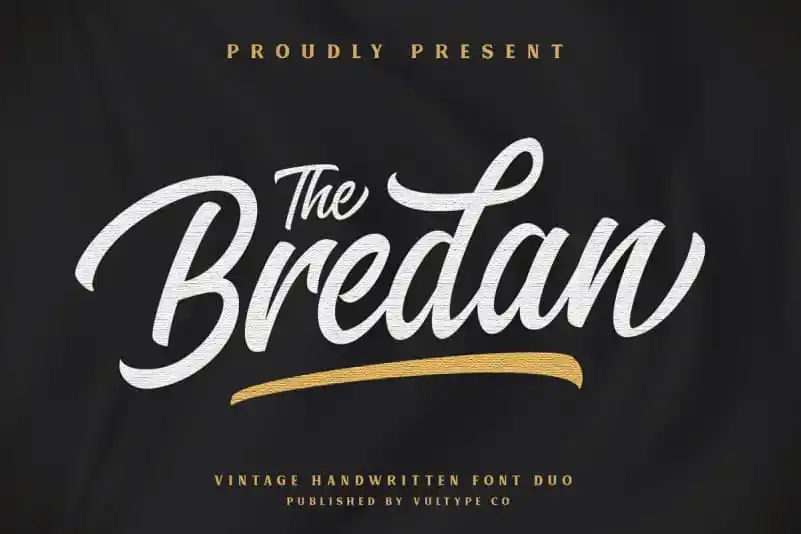
Bredan Font Duo – Download Grátis
Agradeço pela consulta! Estou feliz em apresentar para você a Bredan Font Duo, uma paixanteira dupla de fontes scripts, perfeitamente complementares entre si e projetadas para se harmonizar maravilhosamente. Introduzimos à categoria dos script fonts, a Bredan Font Duo, uma incrível dupla que inclui tanto uma tipografia clássica quanto um estilinho moderno. A Vultype Co. é quem concebeu e compartilhou este projeto fascinante. O design da Bredan Font Duo foi inspirado nos estilos modernos antigos e retro, criando uma fusão de dois elementos em alta demanda: uma tipografia sans-serif com letras bem definidas (modernas) e um script tradicional mais expressivo. Com a Bredan Font Duo, você se encontra diariamente com essa combinação de estilos modernos e vintage. Junte-se ao movimento dos criadores que adotaram este duplo estilo em suas criações, onde o arquétipo moderno capta os momentos atuais, enquanto a tipografia mais tradicional oferece um tom de nostalgia. A Bredan Font Duo é um maravilhoso complemento para seu trabalho gráfico, permitindo que você inovasse e adiciona uma nota de personalização em cada projeto.